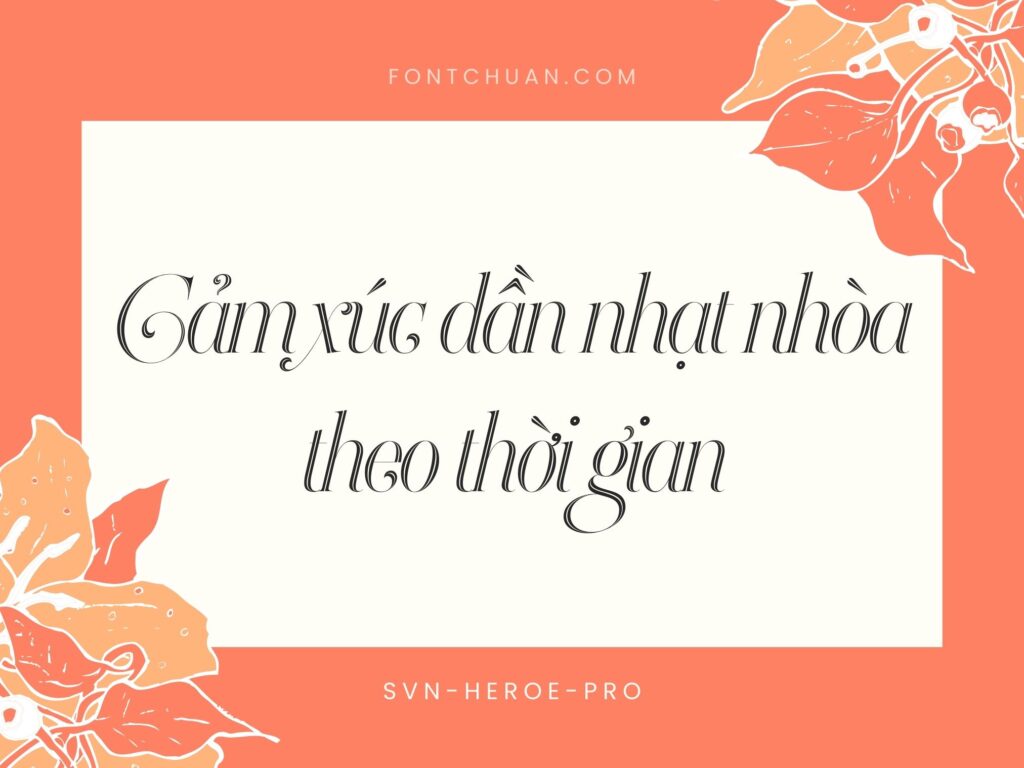
Font SVN Heroe Pro Việt Hóa
Tác giả Font: Lián Types
Heroe là một kiểu chữ serif thanh lịch được thiết kế bởi Maximiliano Sproviero và phát hành bởi Lián Types. Phiên bản gốc của font này đã được Việt hóa bởi Styleno.1 Fonts, hỗ trợ đầy đủ tiếng Việt cùng hơn 100 ngôn ngữ khác. Thành viên của Font Chuẩn đã sưu tầm và chọn lọc font này nhằm đáp ứng nhu cầu đa dạng của bạn đọc và ứng dụng thực tế vào các dự án thiết kế.
Heroe có cấu trúc chữ với các nét thanh mảnh và chân chữ tinh tế, tạo nên vẻ đẹp cổ điển và sang trọng. Font này phù hợp cho các ứng dụng như thiết kế logo, tiêu đề, bao bì sản phẩm cao cấp và các ấn phẩm in ấn. Các ngành nghề như quảng cáo, bất động sản, spa và giáo dục có thể tận dụng Heroe để tạo điểm nhấn độc đáo trong thiết kế.